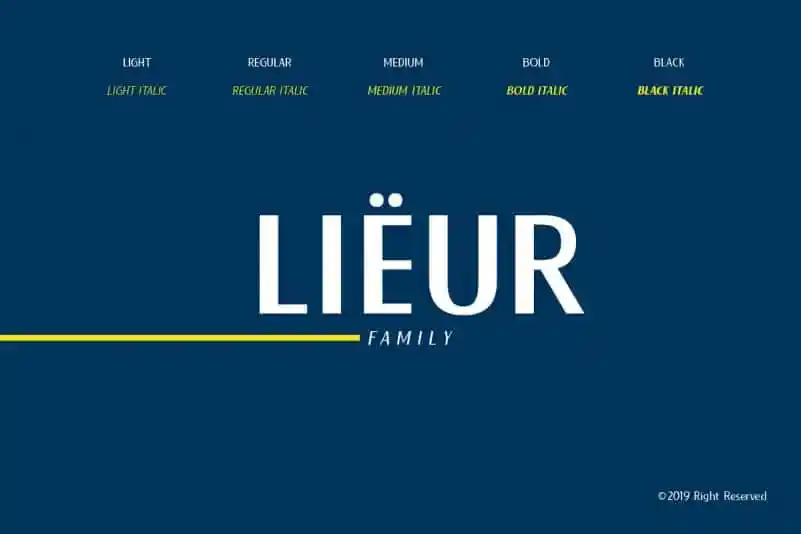
Lieur Sans Serif Font Family – Fonte Grátis
Lieur Sans Serif Font Family
A fonte ‘Lieur Sans Serif’ é uma elegante tipografia sans-serif criada por INKsTYPIA que traz um toque moderno e estilo geométrico minimalista. Perfeita tanto para logomarcas quanto para designs de rótulos, ela também se destaca como uma fonte agradável para texto principal. Além disso, oferece duas tipografias principais: Normal e Italic, que vão do leve até o preto, desde as fuentes Leve até o Bold-Medium-Black. Esta extensa gama de opções garante uma variedade incrível para a criação de designs variados. Seu design minimalista geométrico se adapta facilmente tanto à era contemporânea quanto aos elementos tradicionais dos rótulos e logotipos, fazendo com que seja um recurso visual versátil. Seja você designer gráfico ou um iniciante na criação de arte digital, o ‘Lieur Sans Serif’ é uma fonte que vai agregar valor sem comprometer a harmonia visual em seu trabalho. O design suave e minimalista do ‘Lieur Sans Serif’ faz dele uma excelente escolha para quem busca uma tipografia moderna e elegante, ideal tanto para projetos de logotipo quanto para textos em seções principais. Um recurso valioso para qualquer designer gráfico que deseja oferecer soluções visualmente atraentes e funcionais.